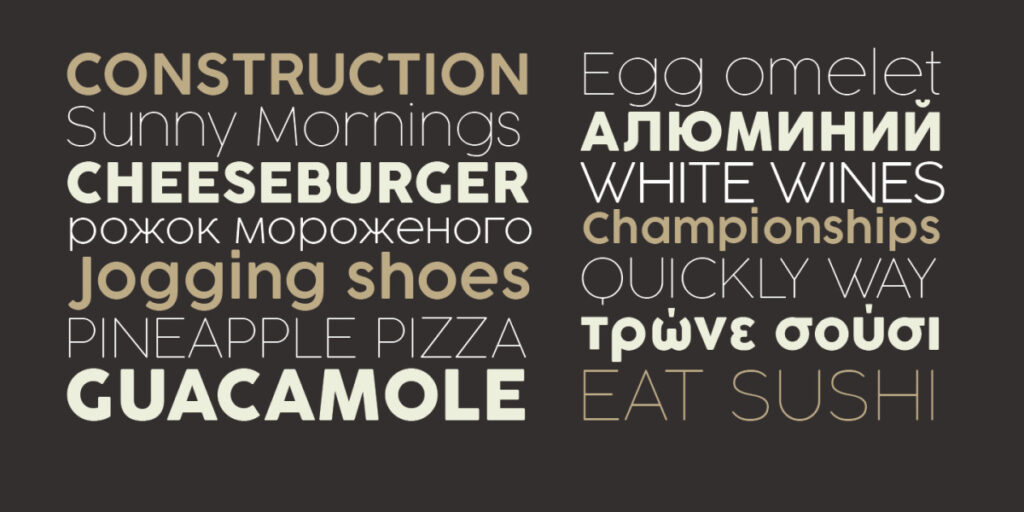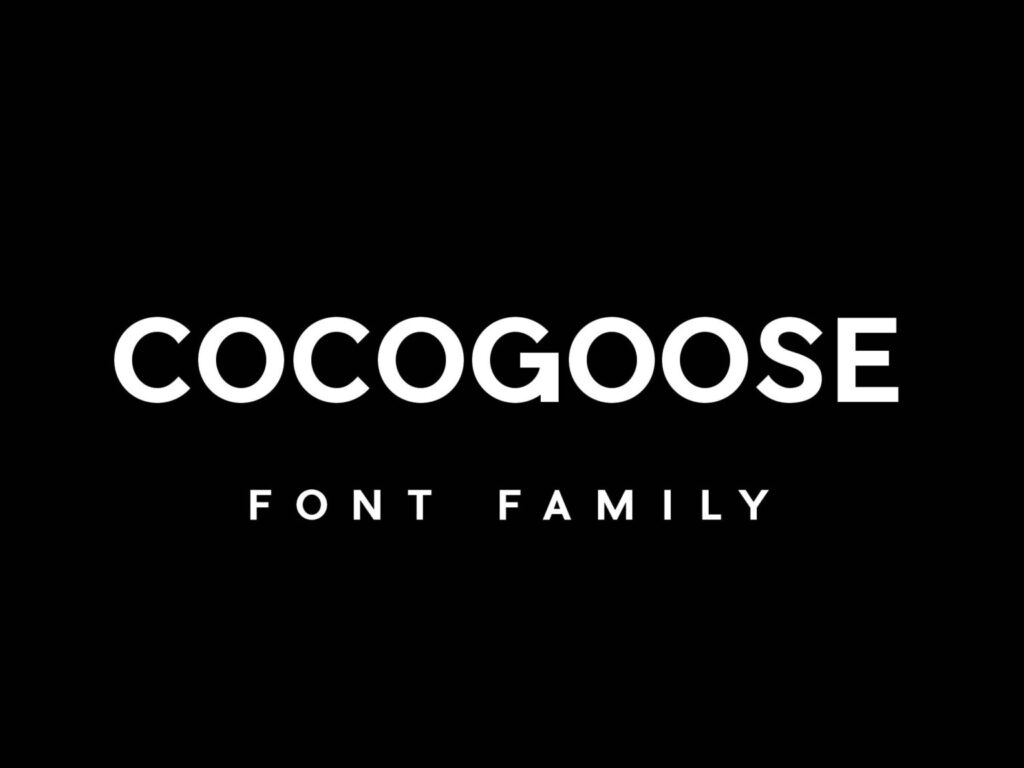
Cocogoose font Việt hóa là bộ phông chữ thuộc dòng Geometric Display Sans-serif nổi tiếng, kết hợp hoàn mỹ giữa kỷ luật hình khối vuông tròn của trường phái Bauhaus và các góc bo mịn màng đầy tính nhân bản. Với cấu trúc nét chữ dày dặn, vững chãi cùng vẻ ngoài đậm chất đương đại, kiểu chữ này giúp các kiến trúc sư, nhà thiết kế kiến tạo diện mạo mạnh mẽ cho các bản vẽ phối cảnh văn phòng container, bìa hồ sơ năng lực hay hệ thống biển hiệu nhà lắp ghép thông minh.
Khối hình học bo tròn và năng lượng thị giác đương đại của Cocogoose font Việt hóa
Điểm cuốn hút của Cocogoose font Việt hóa nằm ở tỷ lệ các ký tự tiệm cận hình tròn hoàn hảo, kết hợp cùng các cạnh bo góc nhẹ nhàng giúp làm dịu đi cảm giác thô ráp của các khối chữ lớn. Cấu trúc chữ sở hữu độ dày nét đồng đều, mang lại khả năng chiếm lĩnh thị giác tức thì và duy trì độ rõ nét vượt trội trên mọi phương tiện truyền thông.
Sự ổn định về mặt thị giác của dòng font này tạo nên cảm giác kiên cố, tin cậy và tràn đầy năng lượng đổi mới. Khi xuất hiện trên các bề mặt vật liệu kiến trúc hiện đại như tấm panel tôn phẳng sơn tĩnh điện, kính cường lực hay nhôm xước trong các công trình nhà lắp ghép thế hệ mới, Cocogoose tạo nên sự tương thích thẩm mỹ cao, phù hợp với phong cách kiến trúc Minimalism hoặc Industrial.
| Phân loại phong cách | Geometric Sans-serif / Rounded Display / Bauhaus |
| Mục đích phù hợp | Biển tên công ty, logo khối hộp, tiêu đề hồ sơ dự án |
Tư vấn từ chuyên viên: Cocogoose sở hữu cấu trúc nét chữ rất đậm và dạng hình khối tròn rộng. Để bản thiết kế đạt hiệu quả thẩm mỹ tốt, bạn nên sử dụng phông chữ này cho các tiêu đề chính, tên công trình hoặc các con số kỹ thuật nổi bật. Phần nội dung mô tả chi tiết nên đi kèm một phông chữ không chân thanh mảnh hơn để người xem tiếp nhận thông tin dễ dàng.
03 Ứng dụng phông chữ Cocogoose vào công trình thực tế
Nhờ vẻ ngoài khỏe khoắn và tính chính xác cao, bộ phông chữ này mang lại giá trị thực tế lớn trong khâu hoàn thiện và quảng bá các dự án xây dựng:
- Hệ thống biển hiệu cho Văn phòng Container và Showroom: Những khối chữ bo góc của Cocogoose rất ăn ý khi gia công chữ nổi bằng inox mạ màu hoặc alu uốn chân gắn đèn LED, giúp mặt tiền công trình toát lên vẻ vững vàng và hiện đại.
- Bìa hồ sơ năng lực dự án kiến trúc: Sử dụng Cocogoose font Việt hóa cho tên dự án giúp tập hồ sơ toát lên vẻ quy chuẩn và đáng tin cậy, tạo niềm tin lớn với các đối tác và chủ đầu tư.
- Hệ thống biển chỉ dẫn phân khu và số phòng: Phông chữ này khi gia công khắc chìm hoặc in UV trên vật liệu kim loại sơn đen mờ sẽ giúp các không gian sinh hoạt trong nhà lắp ghép toát lên chất công nghệ, tạo sự thuận tiện cho người sử dụng khi định vị khu vực.
03 Lưu ý bố cục font Việt hóa Cocogoose đạt độ chuẩn mực và thông thoáng
Để khai thác hiệu quả vẻ đẹp của dòng font hình học này mà không gây cảm giác chật chội cho bản vẽ, người thiết kế nên lưu tâm một số kinh nghiệm sau:
- Nới rộng khoảng cách ký tự: Do các con chữ của Cocogoose có độ nở chiều ngang lớn, bạn nên kéo giãn nhẹ khoảng cách giữa các chữ cái khi viết hoa toàn bộ để câu chữ thông thoáng, tránh hiện tượng dính nét khi quan sát từ cự ly xa.
- Tránh sử dụng cho văn bản dài: Độ đậm nét cao của Cocogoose không phù hợp cho các đoạn thuyết minh kỹ thuật dài. Hãy giới hạn sử dụng cho các cụm từ ngắn từ 2 đến 5 từ hoặc các dãy số hiệu để tạo điểm nhấn thị giác tập trung.
- Lựa chọn gam màu công nghiệp hiện đại: Cocogoose phát huy hiệu quả thị giác cao khi đặt trên các gam màu trung tính công nghiệp như xám bê tông, đen mờ, xanh dương đậm hoặc vàng cảnh báo, làm nổi bật đường nét vuông vức của bộ chữ.